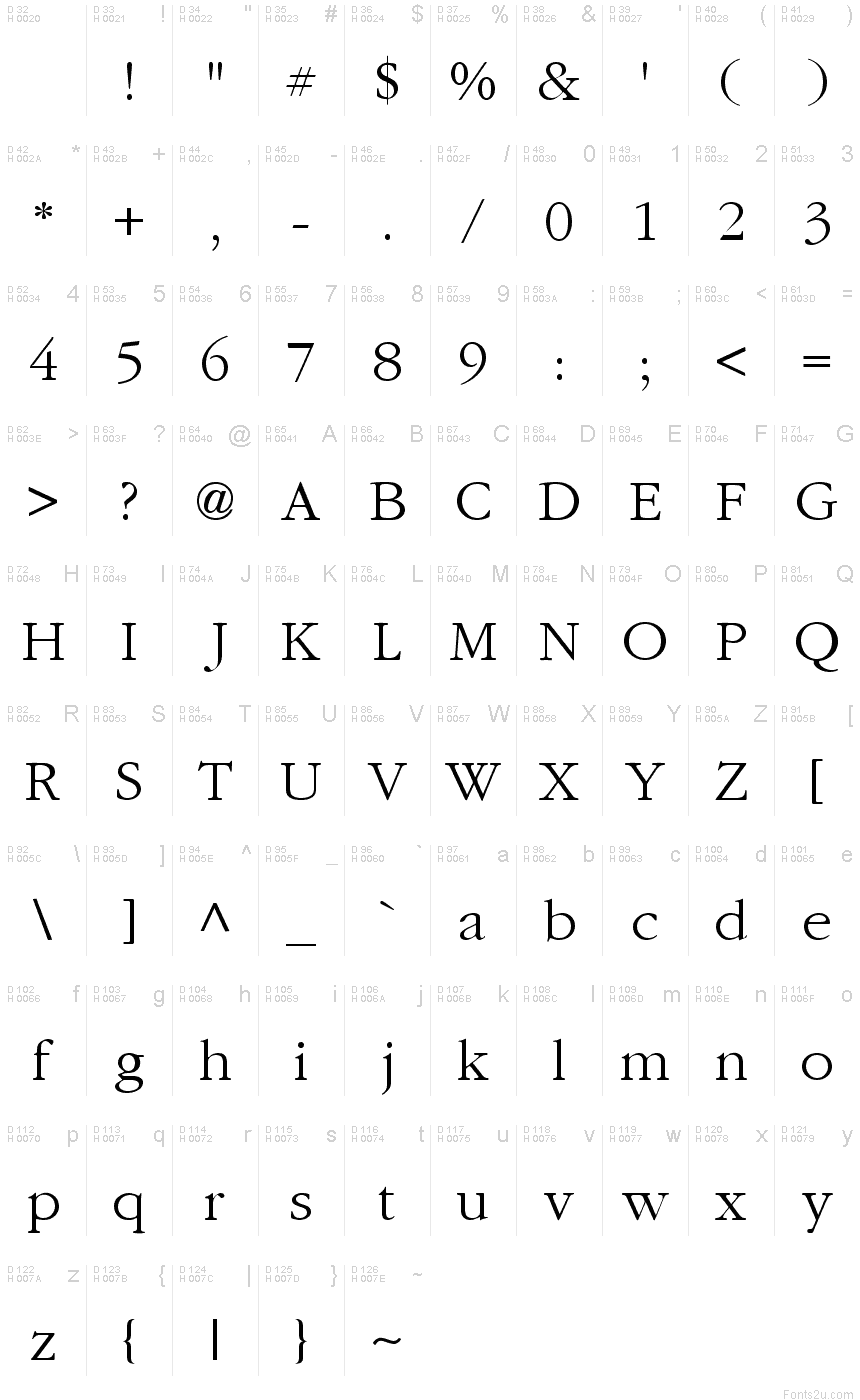
IGaramond Regular
Krój pisma I Garamond od Rubicon Computer Labs Inc. to bezpłatna, klasyczna odmiana szeryfowa. Wnosi ciepło tradycyjnych Garamondów dzięki delikatnie rozszerzonym pociągnięciom, kompaktowym proporcjom i spokojnej, równej teksturze, co sprawia, że akapity stają się płynne i zachęcające, a nie sztywne. Litery mają subtelną elegancję, która wciąż wydaje się solidna, dzięki czemu tekst pięknie trzyma się w rozmiarach czytelniczych, nie wyglądając przy tym na ciasny czy przekombinowany.
Dzięki I Garamond długie fragmenty tekstu zyskują literacki charakter, który doskonale sprawdza się w powieściach, esejach, pracach naukowych i układach redakcyjnych. Ten darmowy font świetnie prezentuje się także w brandingu wydawniczym, plakatach w stylu klasycznym oraz wyrafinowanych materiałach drukowanych, takich jak programy czy broszury. Prosta wskazówka dotycząca łączenia fontów: ustaw tekst główny w IGaramond i połącz go z czystym krojem bezszeryfowym w nagłówkach, aby strona wyglądała ponadczasowo i przejrzyście.